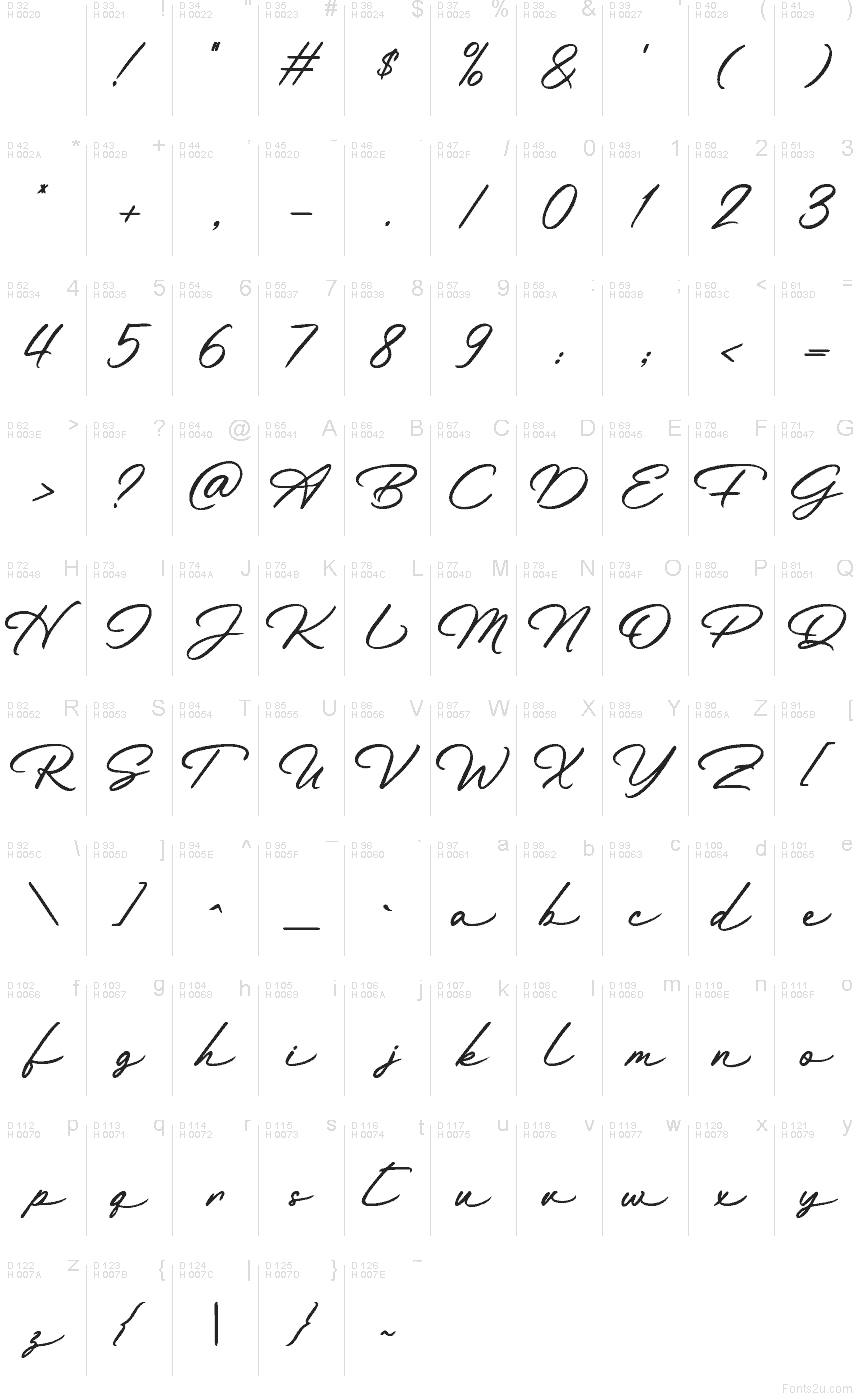
Comptoir de la Gastronomie
Comptoir de la Gastronomie هو خط نصي مكتوب بخط اليد يتميز بضربات طويلة وانسيابية تسمح للحروف بالتحرك عبر السطر بحركة مريحة. تمنحه الانحناءات المفتوحة والزخارف النهائية الممتدة إيقاعاً خفيفاً يشبه لافتات المقاهي أو المتاجر القديمة، بدلاً من مظهر الكتابة اليدوية غير الرسمية.
هذا يجعله خياراً طبيعياً لقوائم المطاعم، وتغليف المخبوزات، وملصقات الزجاجات، وعلامات المتاجر، حيث يحتاج سطر واحد من النص إلى أن يبدو شهياً ومنسقاً. كما أنه مناسب لبطاقات الوصفات أو عناوين مدونات الطعام، لأن منحنياته السخية وتدفقه الثابت يحافظان على نغمة دافئة وذات طابع طهوي مميز.